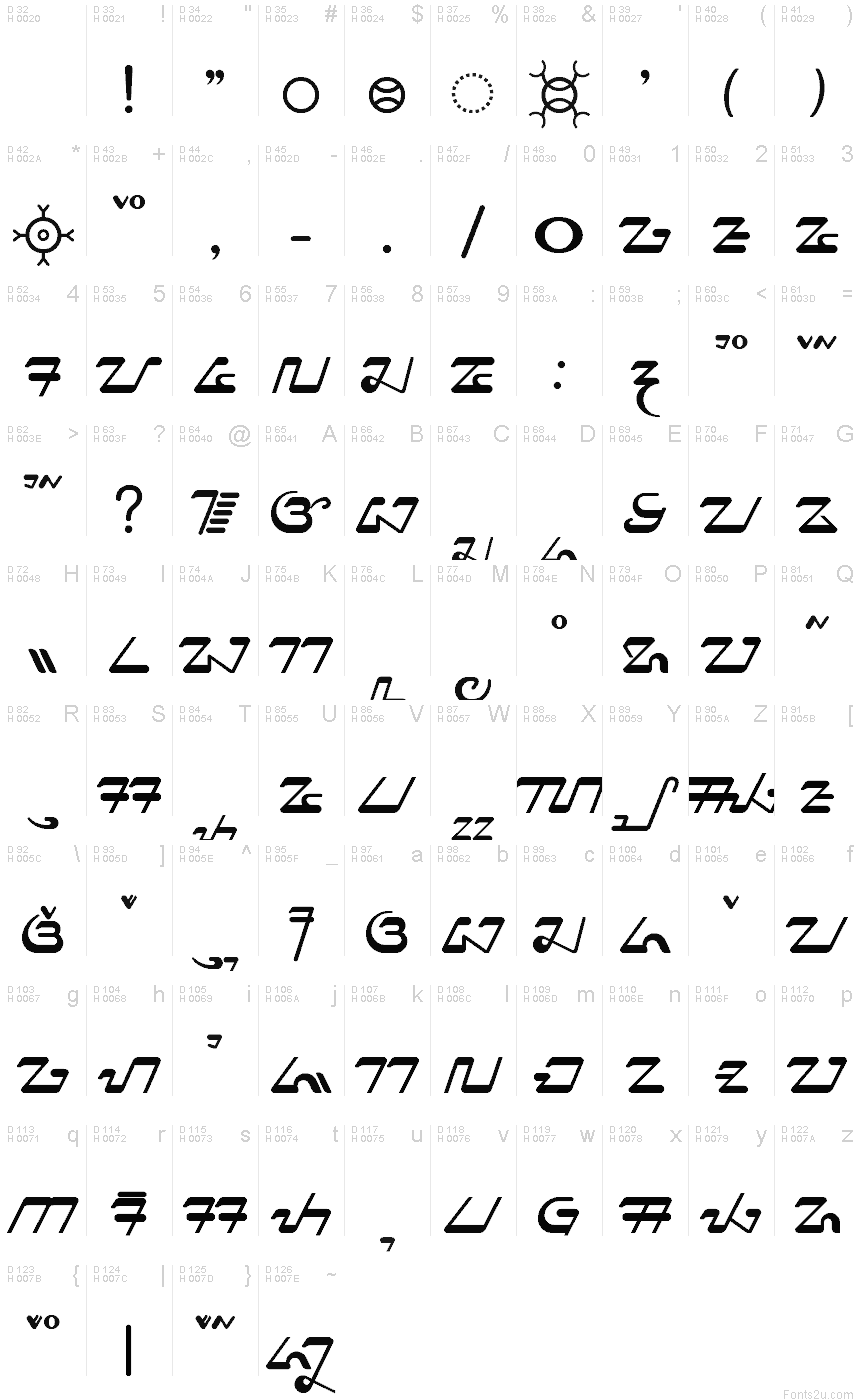
Aksara Sunda Baku nyaéta aksara Sunda kiwari nu diadaptasi ti aksara Sunda kuna. Teu sagemblengna sarua jeung aksara aslina. Aya sababaraha aksara nu dimodifikasi ti aksara aslina. Aya ogé aksara anu beda pisan jeung aksara aslina, contona aksara Nya, Ma, jeung I. Numutkeun filolog anu nyieun aksara ieu, tujuannya taya lian supaya barudak kiwari gampang ngalarapkeunna. Salian ti éta ogé keur ngagampangkeun merenahkeun disain fontna. Sakitu..